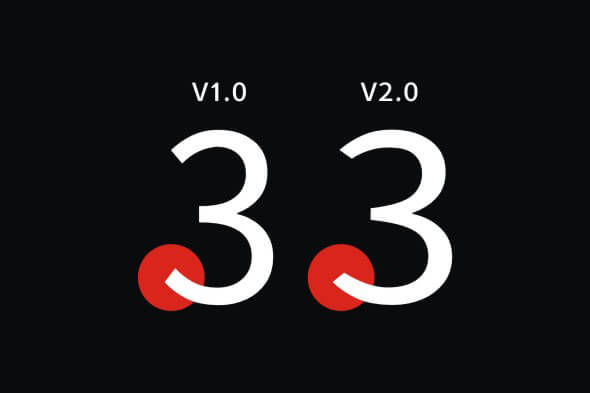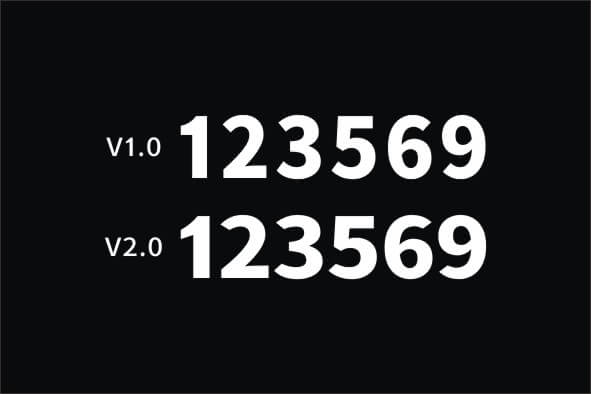
江城黑体:基于思源黑体优化数字重心平衡的黑体字形
字体作者:刘鹏 (中国大陆) 字体字重:7个
江城黑体是基于思源黑体改造。江城系列字体作者刘鹏观察发现,带有下面的横数字“1”非常适合屏幕显示,但并不适合物料印刷等材质上的呈现。所以刘鹏把思源黑体的数字“1”去掉下面的横,并优化数字重心平衡,及间隔空隙,解决了数字均匀问题。并调整字符范围,让该字体在PS、AI等软件中显示在中文区,更方便设计师寻找。当然,以上只是刘鹏个人观点,具体网友可按个人喜好选择。
Ver 2.1 (2021/10/28)
• 以IBMPlexSans为基础,重新修改了字体西文数字
• 新增斜体版本,以代替江城斜黑体
Ver 2.0 (2020/12/24)
• 重新优化调整了字体西文数字,让字体更稳重,末端更流畅
• 重新调整了字体字重显示方式,700W、900W更改为600W、700W
• 调整了字体名称信息设置,增加了英文名称,让该字体跨系统Linux系统下名称显示正常
Ver 1.0 (2020/06/24)
• 江城黑体正式发布
中文字体符号没有做全
而且横看起来较粗
小字重下的数字1看起来比较偏右下,希望能修复一下
数字改了,英文也顺便改一下吧,像C G J Q S a c e f g j l r s t这些,以及它们的变体,都需要修改一下,否则太不统一了
2.0 中的数字看起来反而丑了……
• 尴尬,这黑体我自己也在用,数字也是按自己喜欢修改的
新版主要改了英文数字,样例你没换
江城黑体更新V2.0版本了!
1、重新优化调整了字体西文数字,让字体更稳重,末端更流畅
2、重新调整了字体字重显示方式,700W、900W更改为600W、700W
3、调整了字体名称信息设置,增加了英文名称
能出一款1下面带一横的吗?思源黑体在CDRX6以上版本拖动会有闪动错位, 刘鹏大神改过的字体不会很平很好用